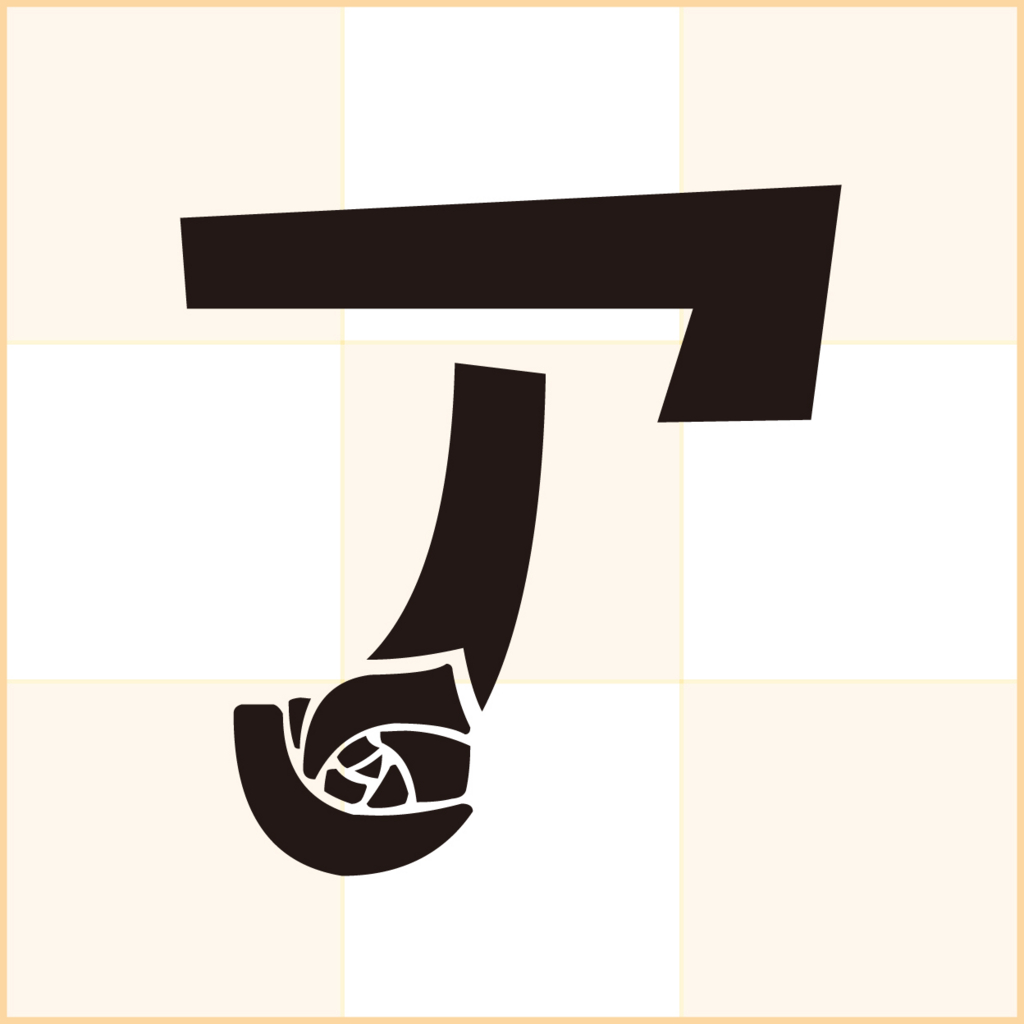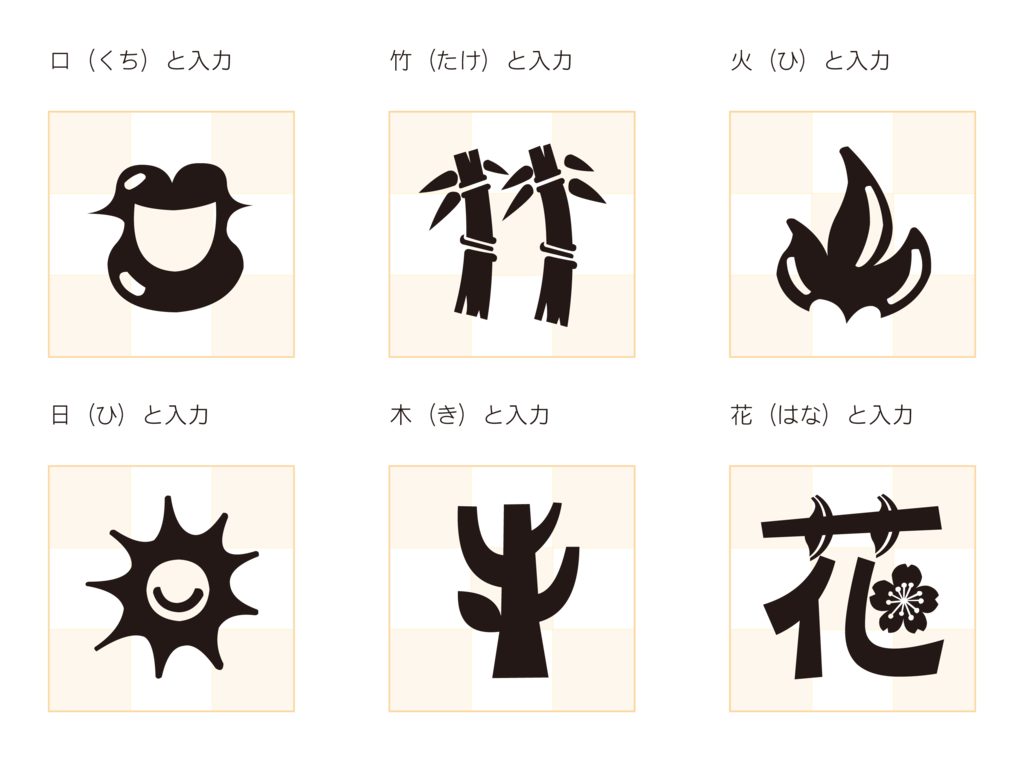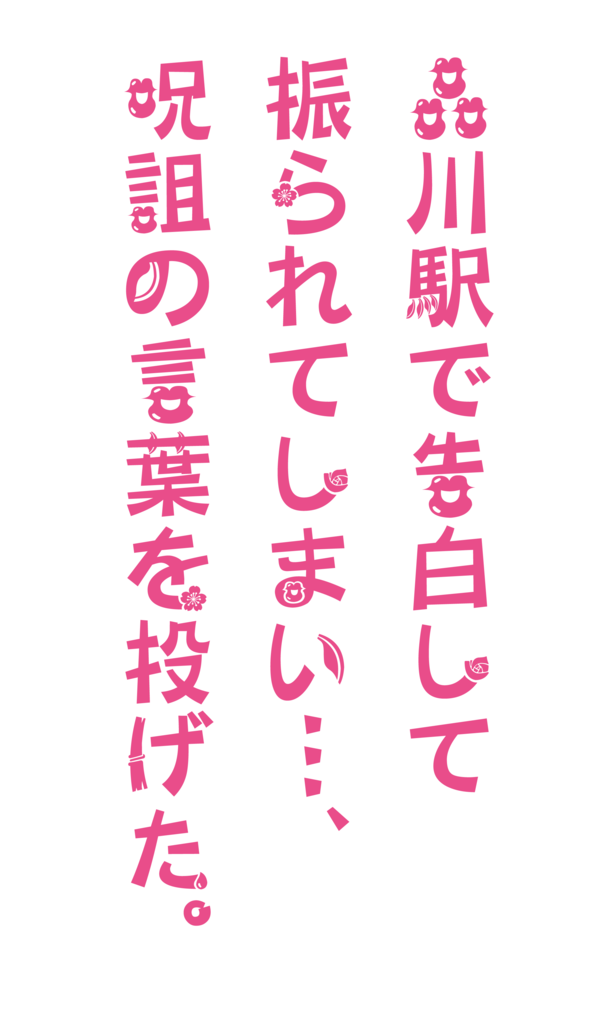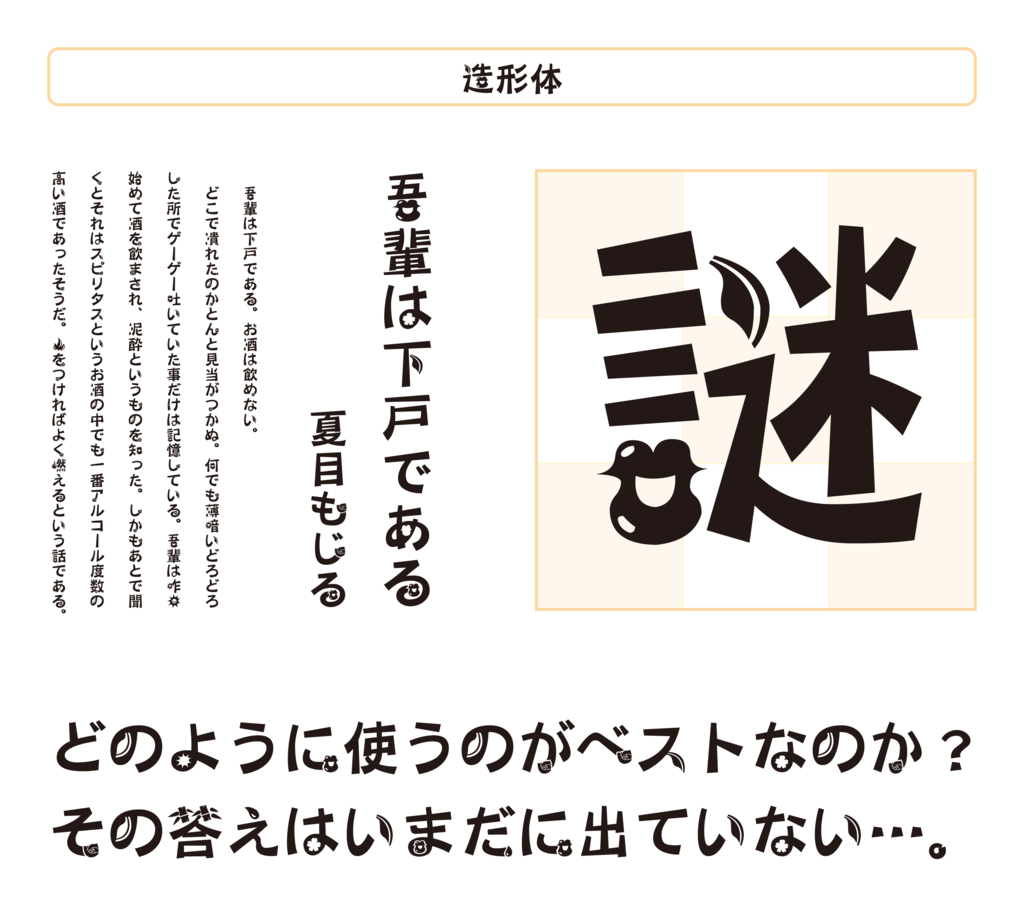
造形体
造形体は説明が難しいフォントだ。口(くち)と入力すると唇になり、竹(たけ)と入力すると竹が生える…。そのまんまの意味だが、意味が分からないかもしれないので画像を貼り付けてみた。
「造形体」は、ダイナフォントのその弾けたセンスが弾けきったインパクト大のフォントだが、一体、どういう場面で使用すれば良いかはまるで謎だ。
上記はイラストではなく、入力して変換した際に表示されたれっきとしたフォントである。
どのような使用方法が正しいのか使い勝手は相当な難易度だが、とにかく口のインパクトはかなりすごい。
造形体の書体見本